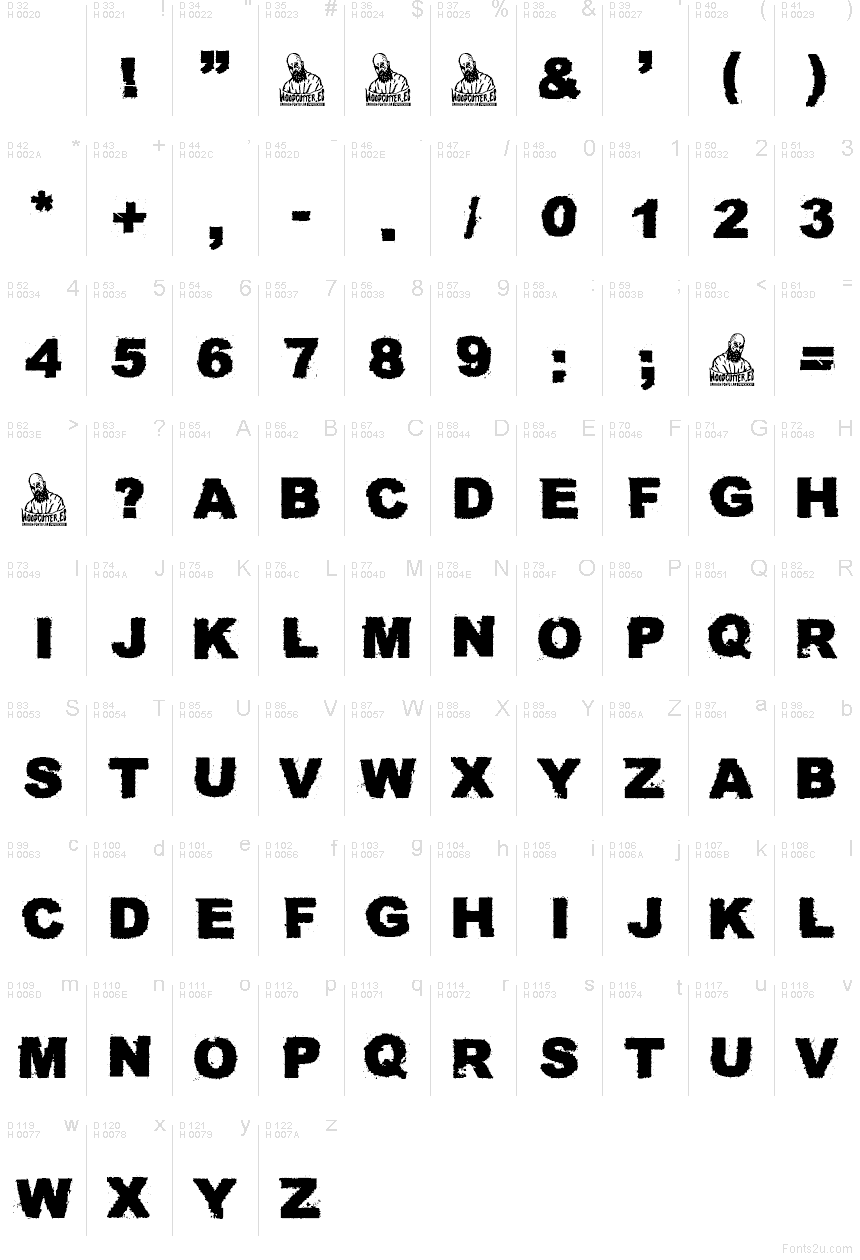
La Super Destrozada
La Super Destrozada di Woodcutter Manero è un font display gratuito dallo stile eroso, perfetto per poster dal carattere graffiante e vissuto. Le lettere appaiono squadrate e decise, ma i loro bordi sono mangiati e ricoperti di granulosità, conferendo all'intero carattere l'aspetto di carta strappata, inchiostro consumato o di una grafica murale rovinata dalle intemperie.
È ideale per flyer musicali, titoli horror, branding streetwear, copertine di fanzine, poster di protesta e titoli dall'aspetto grezzo dove l'impatto conta più della rifinitura. Essendo un font gratuito, funziona benissimo anche per brevi titoli, prove di logo e monogrammi, poiché le forme pesanti mantengono la loro forza anche quando la trama le frammenta.